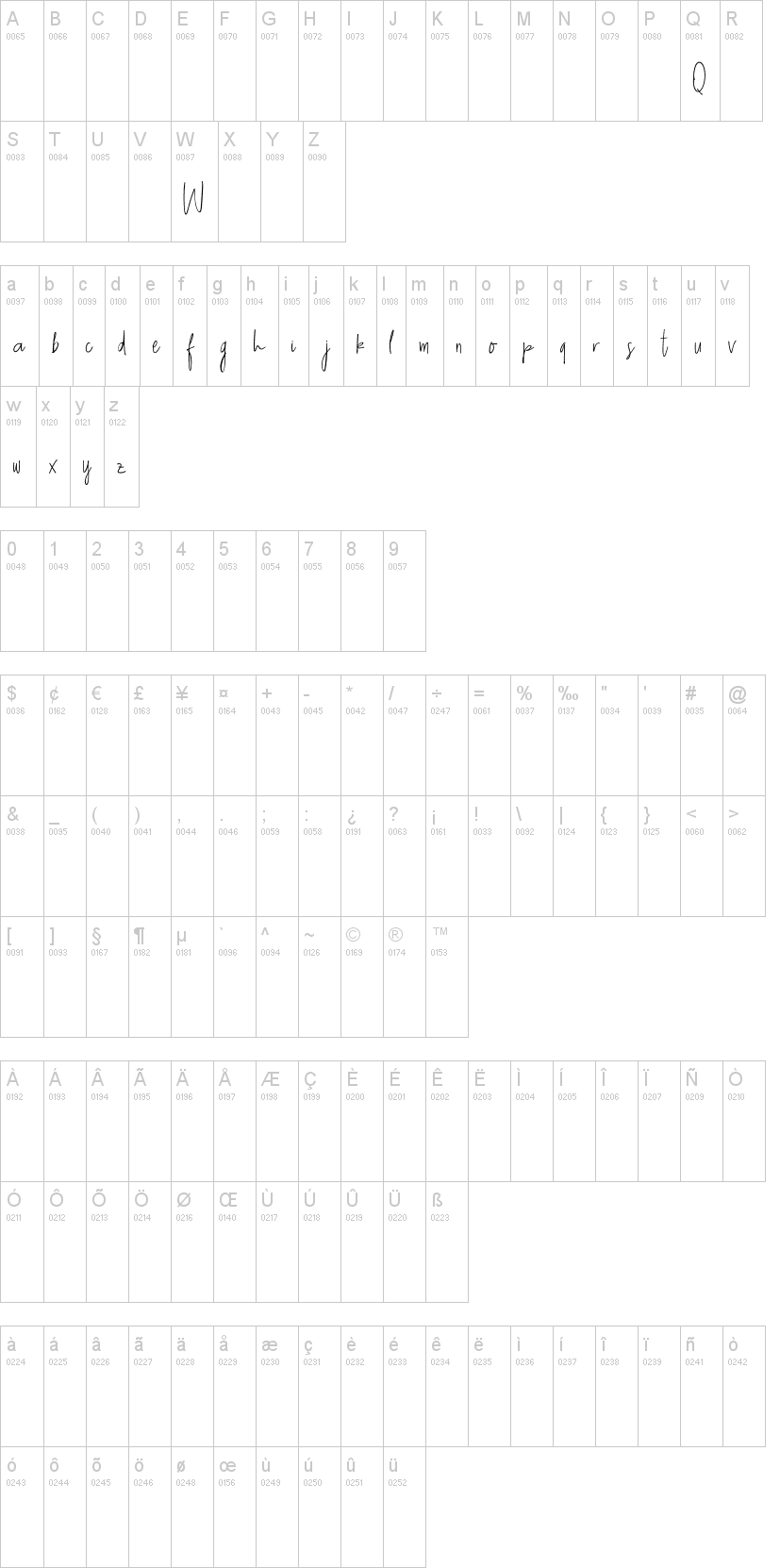
Queen Waffle
Queen Waffle 字体是一款由 Andrew Paglinawan 设计的手写体字体。它的设计灵感来自于一个古老的英国传统食品,即热金饼,它的外观温柔而活泼,给人以温暖的感觉。Queen Waffle 字体的特点是它可以自由地改变字体的宽度,可以在文本中添加不同的效果,以及可以调整字体的大小。这款字体适用于各种不同的场景,如招牌、标志、海报、宣传单等,可以让您的作品更加生动有趣。
Queen Waffle是一款非常不错的手写艺术字体,具有很好的视觉感,适合于文化类的宣传设计、商业类品牌的广告和产品包装设计以及个性化文字排版等较多场景。
Queen Waffle字符映射图